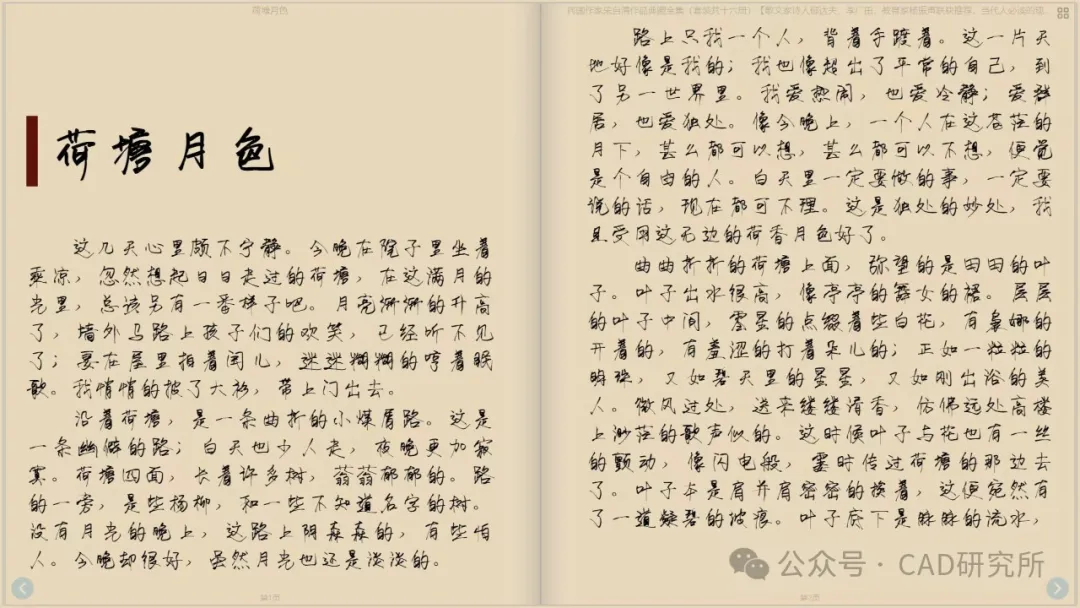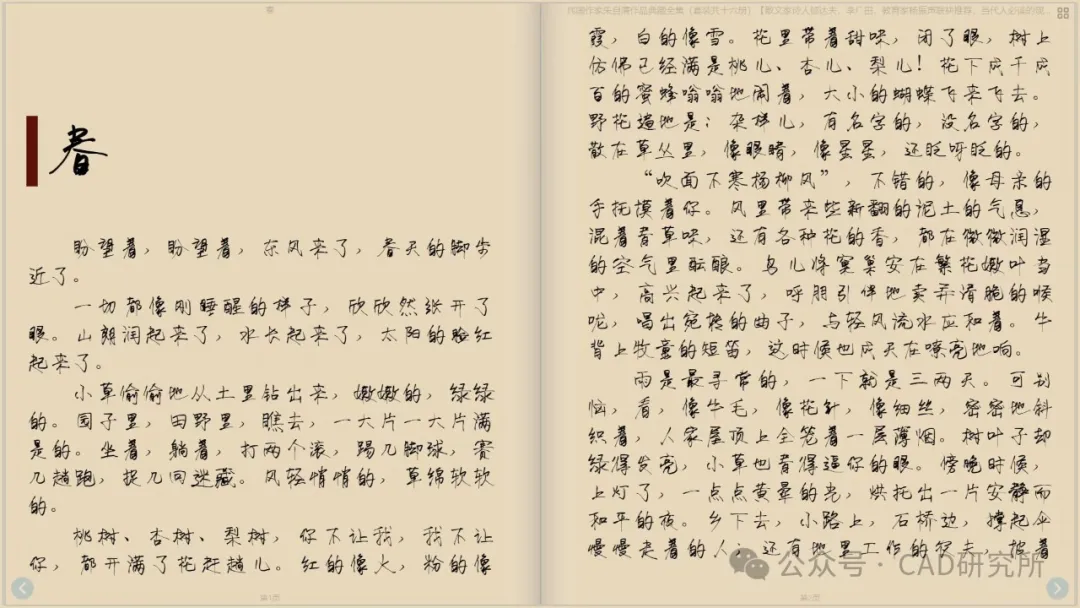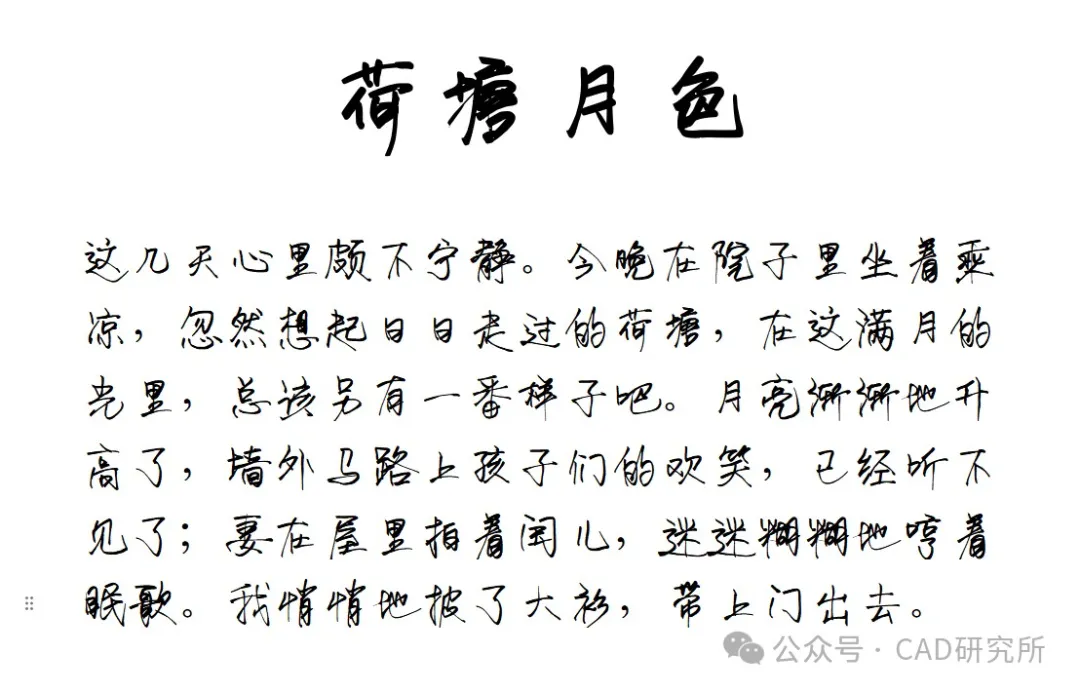
荷塘月色手写体下载,一款可以替代手绘文字的免费商用手写字体
荷塘月色手写体是公众号CAD研究所作者在其平台发布的一款免费可商用手写字体。作者是一名深化设计师,平时在工作中需要经常手绘线条和文字,有时候文字较多就会很费时费力,于是就决定设计这样一款手写体。
在创作过程中,设计师精心挑选了朱自清的《荷塘月色》进行参考书写,顺便测试排版效果。文章中的情感与意境,与设计师对于家庭与工作的情感寄托不谋而合,使得这款字体在诞生之初便蕴含着浓厚的情感色彩,这也是这款字体名字的由来。因此,“荷塘月色手写体”不仅是一款字体,更是一种情感的传递。